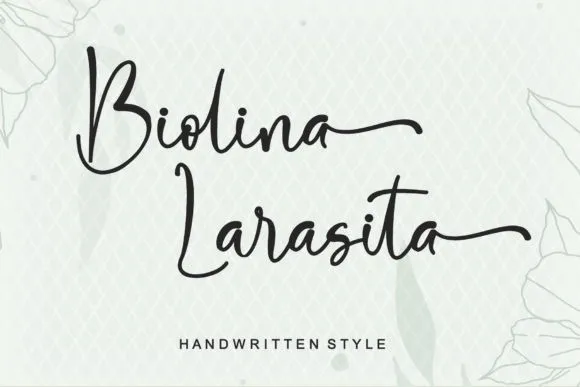
A BioLina Larasita é uma fonte script moderna criada pelo Letterafa Studio com acréscimos de traços que remetem a uma escrita à mão, oferecendo um toque sofisticado e sujo na mistura do pincel. Esta fonte traz um brilho luxuoso para qualquer projeto design que você possa conceber! Com PUA (Propriedades Unicode Associadas) codificadas, você pode acessar com facilidade todos os incríveis gílios e ligaturas que essa fonte tem a oferecer. A BioLina Larasita é perfeita para aqueles que buscam um toque diferenciado em seus projetos de design gráfico, adicionando uma elegância única ao seu trabalho final. Seja em impressões digitais ou físicas, ela traz profundidade e personalidade a qualquer tipo de arte visual.